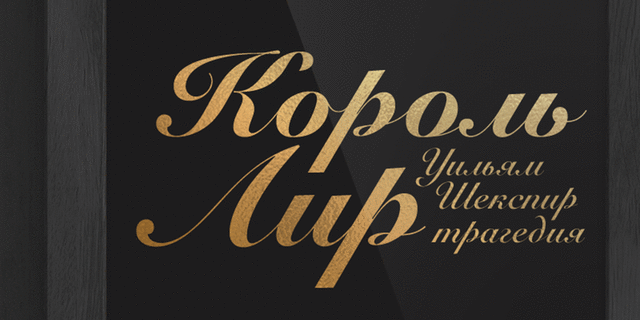
Шрифт Roundhand (Раундхэнд) был разработан Мэтью Картером в 1966 году на базе образцов рукописных шрифтов Чарльза Снелла — английского каллиграфа конца XVII – начала XVIII веков, известного, в частности, сочинением «The Pen-man’s Treasury Open’d». Шрифт имеет высокий контраст с резкими переходами от тонких штрихов к толстым, регулярный наклон знаков и округлые формы. Прописные знаки нередко используются в качестве инициалов в сочетании с другими шрифтами. В цифровой версии шрифт представлен тремя начертаниями разной насыщенности. Предназначен для не очень длинных текстов и заголовков. Будет уместен в различных приглашениях, адресах, ресторанных меню и прочей акциденции, стремящейся подчеркнуть благородный и изысканный характер содержания. Кириллическая версия спроектирована Владимиром Ефимовым и Изабеллой Чаевой. Выпущена компанией ПараТайп в 2013 году.
Функции начертания Roundhand BlackПрименение в макете:
Ассоциации c начертанием Roundhand BlackКачества и характер:
классический, старомодный, традиционный, праздничный, торжественный, вкусный, приятный, вежливый, лиричный, старательный, мастерский, красивый, прекрасный, аккуратный, музыкальный, звонкий, изящный, элегантный, аристократичный, благородный, манерный, бальный, салонный, комильфо, приличный, серебристый, золотой, блестящий, роскошный, светский, художественный, ритмичный, нарядный, изысканный, утонченный, романтичный, грациозный, свадебный, броский, помпезный, новогодний, богатый, исторический, страстный, творческий, сексуальный, осенний, фантастичный, гламурный, рождественский
балет, опера, искусство, выставка, конфеты, десерт, ресторан, роскошь, гравировка, свадьба, салон, поэзия, музыка, симфония, бал, вальс, сольфеджио, ноты, татуировка, тату, подарки, цветы, торт, праздник, украшение, кондитерская, сладости, рождество, парикмахерская, Новый Год, кафе, мода, булочная, любовь, чай, вино, комильфо, кофе, обед, ужин, романтика, платье, одежда, Christmas, кухня, селфи, красота, осень, живопись, трофей, награда, бутик, инстаграм, гламур, концерт Стилистика: